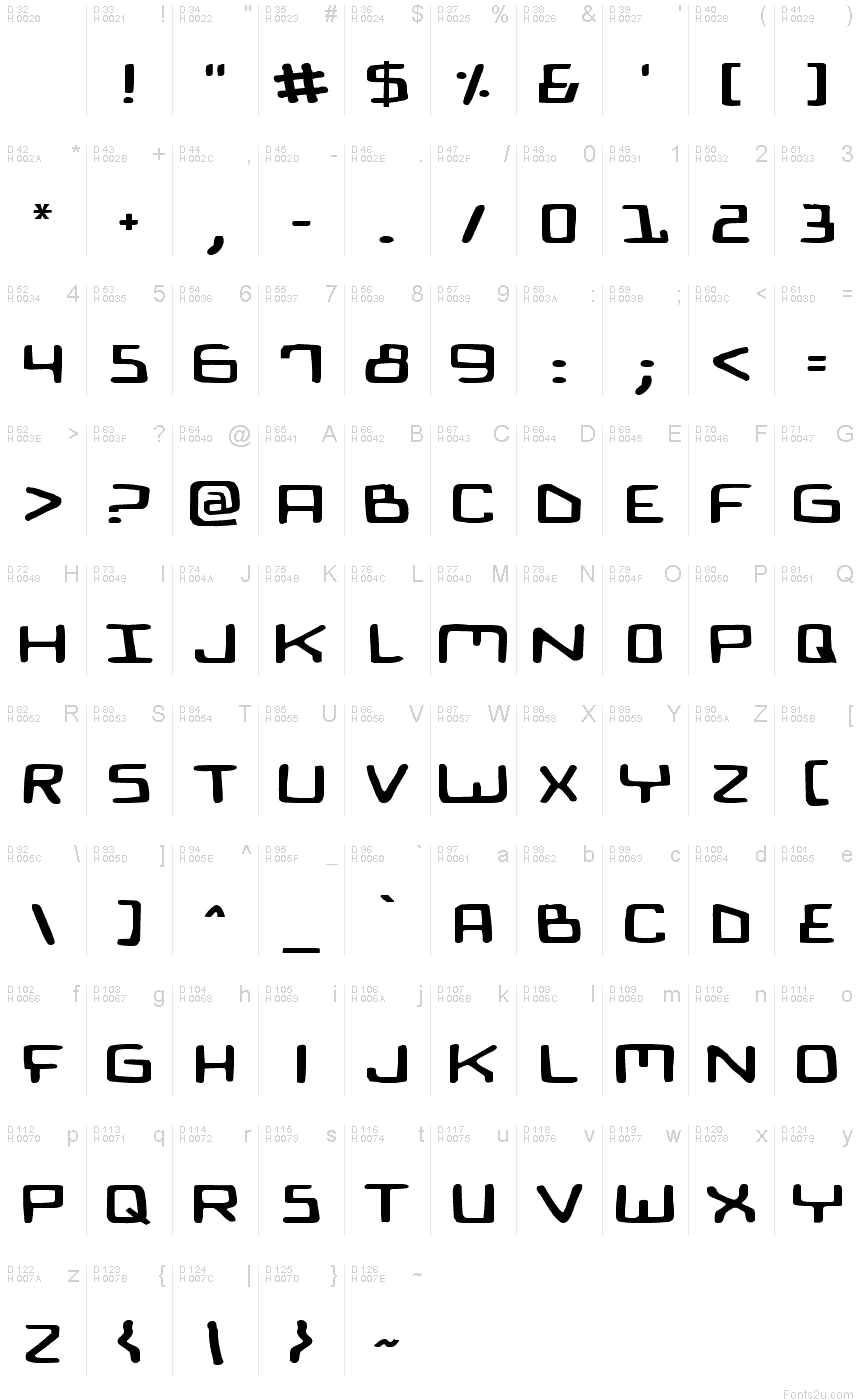
Náhled písma Bionic Comic Expanded
Bionic Comic Expanded od Daniela Zadoroznyho z Iconian Fonts je bezplatné komiksové display písmo. Jeho robustní, hranaté křivky a lehce mechanické tvary působí jako nápisy přímo ze sci-fi komiksu – jsou výrazné, přátelské a lehce futuristické. Díky větší šířce mají slova prostor k dýchání, zatímco silné tahy a zaoblené rohy udržují hravý a přístupný dojem, aniž by působily chladně či příliš technicky.
S Bionic Comic Expanded budou titulky na obálkách komiksů, herních logách, náhledech videí na YouTube, obalech hraček, plakátech na akce i dětských pracovních listech okamžitě fungovat. Toto bezplatné písmo vyniká ve velkých velikostech, kde jeho výrazný rytmus a otevřené rozestupy dokážou prorazit i skrze rušnou grafiku. Pro doplňkový text ho kombinujte s čistým, neutrálním bezpatkovým písmem a nechte Bionic Comic Expanded, aby vyniklo v hlasitých a energických nadpisech.
Mapa znaků písma Bionic Comic Expanded
Mapa znaků písma Bionic Comic Expanded: Základní latinka, strana 1
Glyfy písma Bionic Comic Expanded — Základní latinka, strana 1